오늘은 완성도 높은 서체에 대해 이야기해볼까 합니다.
완성도의 사전적 의미는 '어떤 일이나 예술 작품 따위가 질적으로 완성된 정도'입니다.
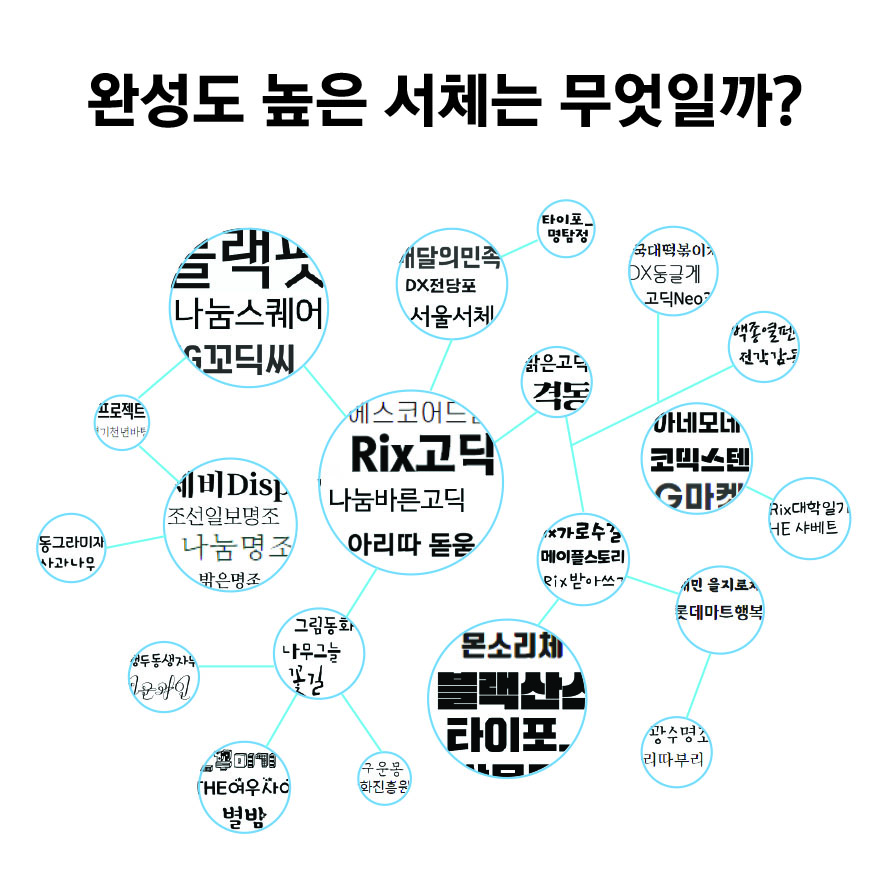
| 폰트에서의 완성도는 무엇을 의미할까?
폰트 디자인을 22년 해오면서 계속 고민하고 있는 부분입니다. 가독성이 높은 글자들과 글줄(여러 글자를 잇따라 써서 이루어진 줄), 공간의 최적화, 자소 형태의 유려함,.. 등의 용어가 생각납니다. 말로 표현하기 어려운 요소들이고, 디자인을 전공했다고 하더라도 잘 와닿지 않을 거라 생각됩니다.
이것은 폰트 디자이너의 생각이지 폰트를 사용하는 유저 입장과 다르다는 것을 오래 일하면서 더 잘 알게 되었습니다. 폰트와 사람이 닮은 점이 많다는 점도 같이 알게 되었습니다. 사람마다 각자 미의 기준이 다르고 취향이 다르듯, 폰트도 사람과 유사한 속성이 있다는 것이죠. 객관적으로 잘생기고 예뻐 보이지만 내 눈에만 잘생기고 예뻐 보일 수도 있고, 못생겼지만 매력적일 수도 있습니다. 가장 중요한 것은 어떠한 자리에서 어떤 옷을 입고, 어떤 행동과 말을 하느냐에 따라 그 사람이 달라 보인다는 것입니다. 폰트도 비록 객관적으로 못생겨 보이는 서체이지만, 콘셉트에 부합되는 곳에서 그 디자인을 빛낼 수 있는 서체라면 완성도 있는 서체라고 말할 수 있습니다.
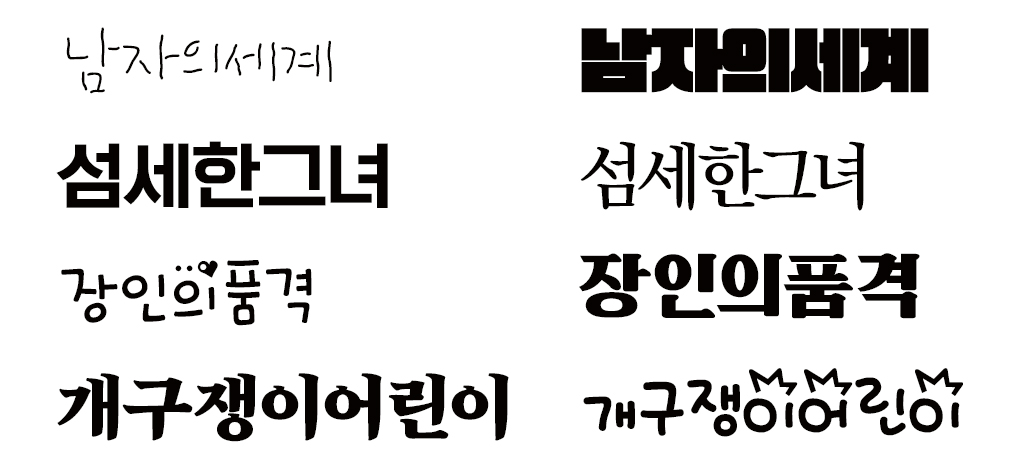
물론 고딕류나 명조류끼리 상대적으로 완성도 높은 서체를 가늠할 수 있습니다. 위에서 말한대로 글줄이 잘 정리되어 있는가? 혹은 공간 구성이 가독성 높게 잘 생성되어 있는가.. 하는 식으로 말입니다. 완성도를 가독성 측면으로 볼 것인가, 아니면 구조적 측면으로서의 완성도만 볼 것인가에 따라 또 달라집니다. 세부적으로 따지고 들어간다면 끝이 없을 거라 생각됩니다. 폰트가 워낙 많이 나와서 더 이상 새로운 디자인이 나올 수 없을 것 같지만, 폰트 디자인의 세계는 굉장히 넓고 깊어서 앞으로도 계속 새로운 디자인이 나올 것으로 생각됩니다.
폰트는 디자인 결과물 내에 하나의 소스입니다. 화려해야 하는 상황에서는 화려한 폰트가, 가독성이 최상인 폰트가 필요할 때는 읽기 좋은 폰트가, 굉장히 두꺼운 서체가 필요할 경우는 두꺼운 폰트가, 촌스러운 서체가 필요할 경우는 촌스러운 느낌을 주는 폰트가 완성도가 높다고 말할 수 있습니다. 결론적으로 다시 말하자면, 폰트에서 완성도 높은 서체란 디자인 콘셉트에 폰트가 정확히 부합되었을 때 완성도 높은 서체라고 생각합니다.